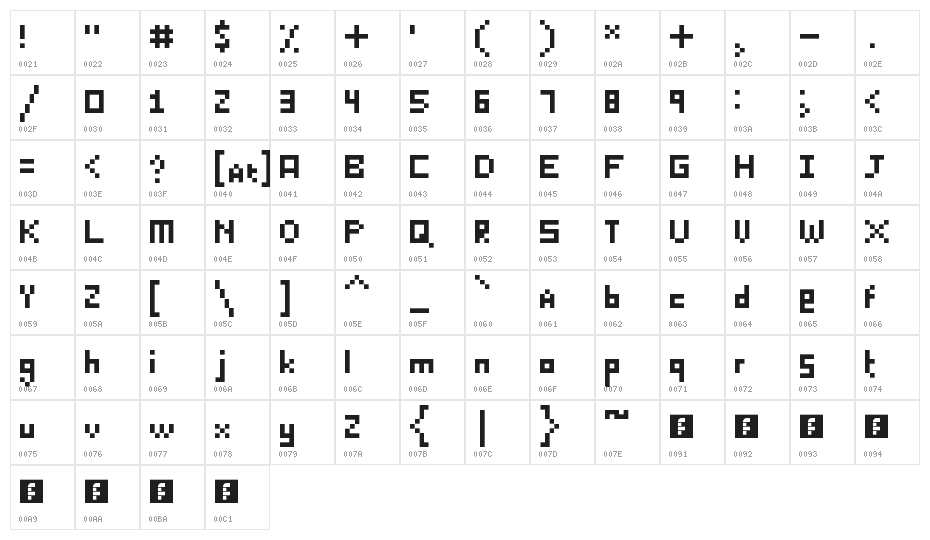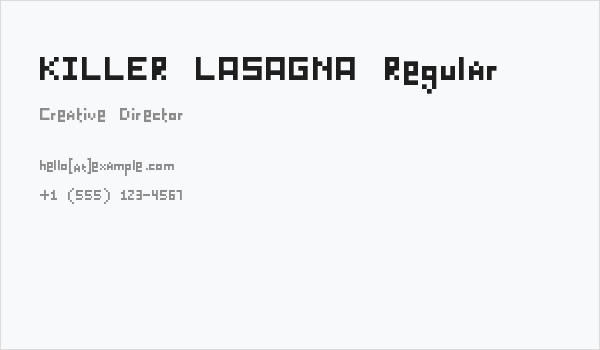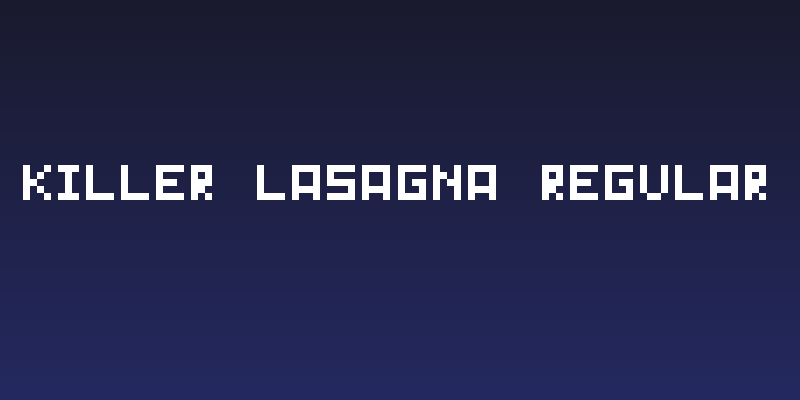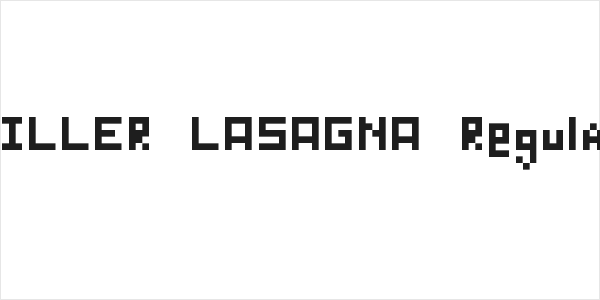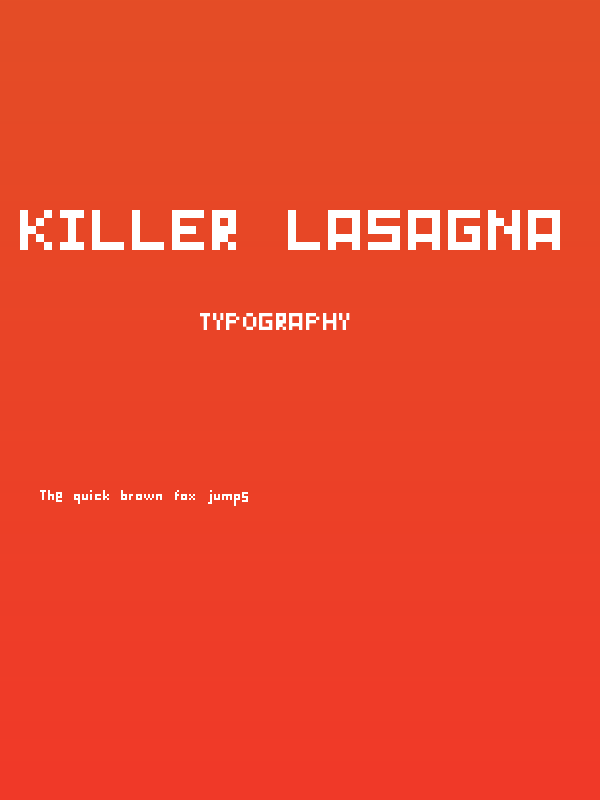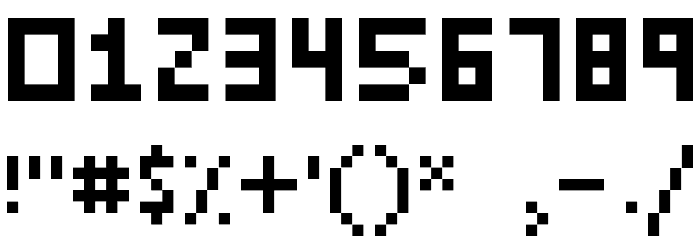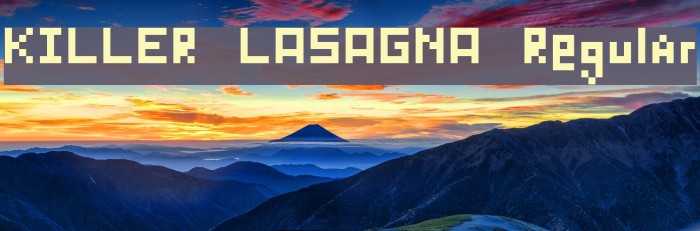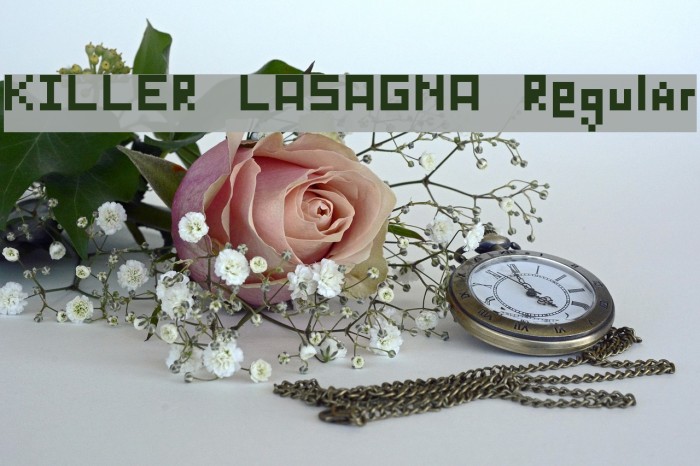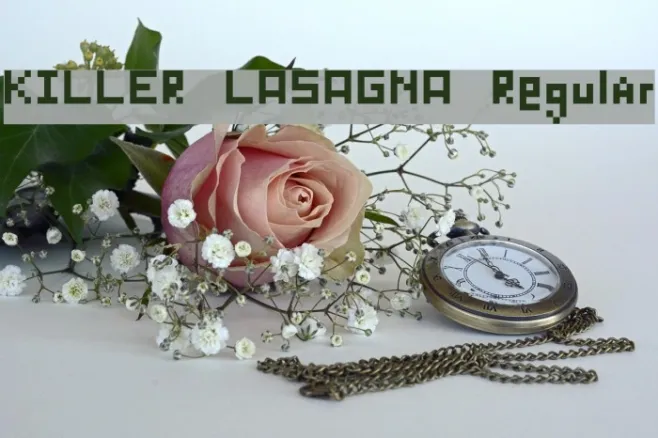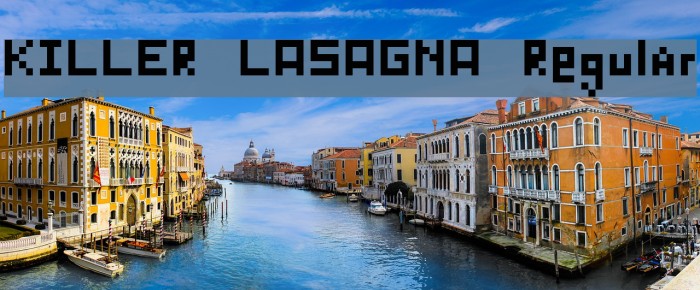
KILLER LASAGNA Regular Font
| Stile generale | Retro, Digital |
| Caso d'uso | Headlines, Logos, Digital Art |
| Progetti proposti | Ideal for retro video game designs, digital art projects, or any creative work that seeks to capture a vintage digital feel. |